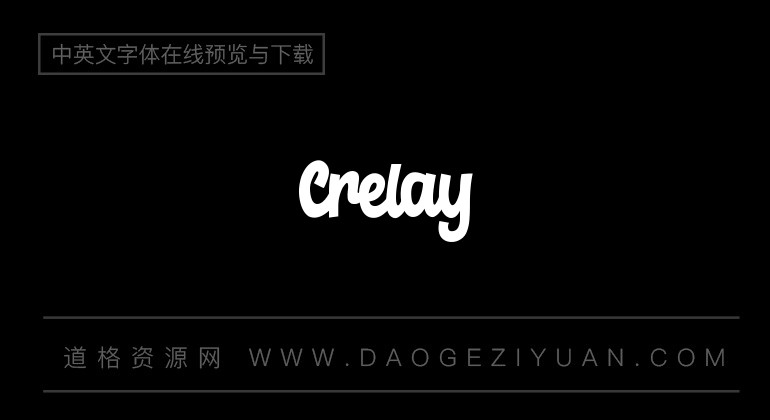
Crelay
Crelay 字体是一款简洁、易读的英文字体,由英国设计师Richard Robinson设计。它有一种清新的外观,采用圆润的字形,拥有自然的流动感,加上新颖的设计,给人以清新、自然的感觉。Crelay字体可用于多种应用,包括网页设计、平面设计、印刷品等,适用于大多数英文文本的排版。
Crelay是一款非常不错的手写艺术字体,具有很好的视觉感,适合于文化类的宣传设计、商业类品牌的广告和产品包装设计以及个性化文字排版等较多场景。